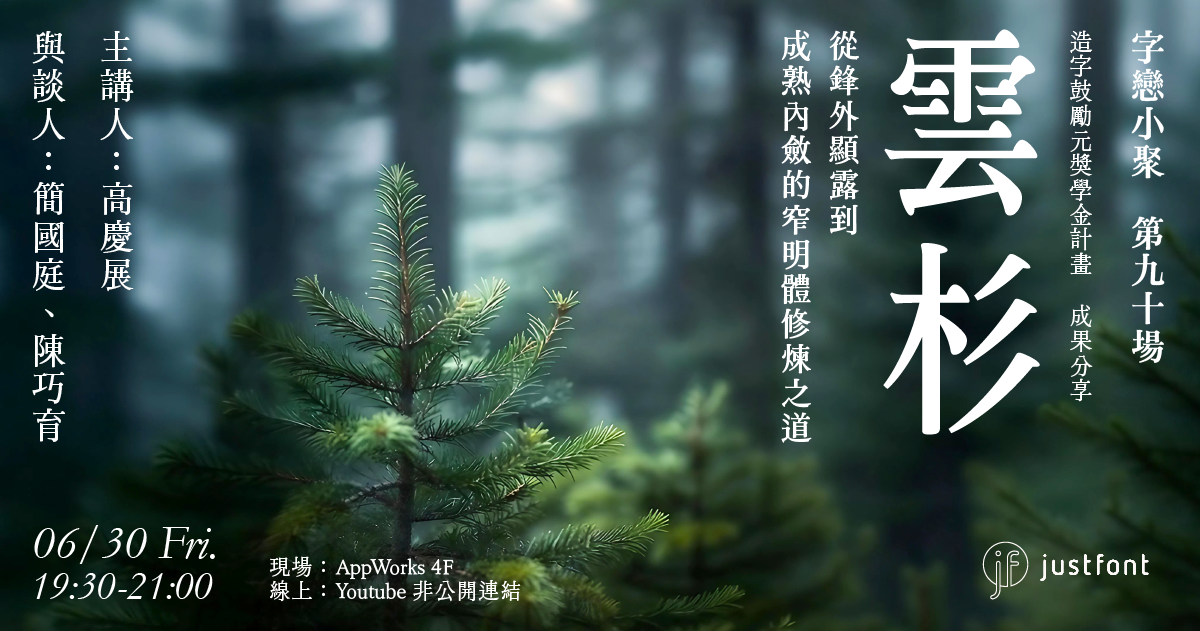
造字鼓勵元第六屆首獎得主高慶展以「武俠體」提案與對字體設計的熱情,獲得評審青睞,並開啟半年以上的設計輔導。
慶展在初期以武俠打鬥經典場景為靈感,在文字上融入竹林、刀劍等造形要素,提出窄明體的設計。在輔導期間,深入琢磨窄明體的設計概念,最終蛻變成為沈穩內斂的「雲杉」。
本場小聚,慶展將分享他為何、又如何在字體修煉之道上,將鋒芒外顯、裝飾性強的「武俠體」,細細煉就成狀似沈靜,但仍氣宇軒昂的「雲杉」。
- 慶展個人的造字學習歷程
- 「武俠體」設計概念與歷程
- 「雲杉」的細節與調整過程
- 鼓勵元輔導心得與後續計畫